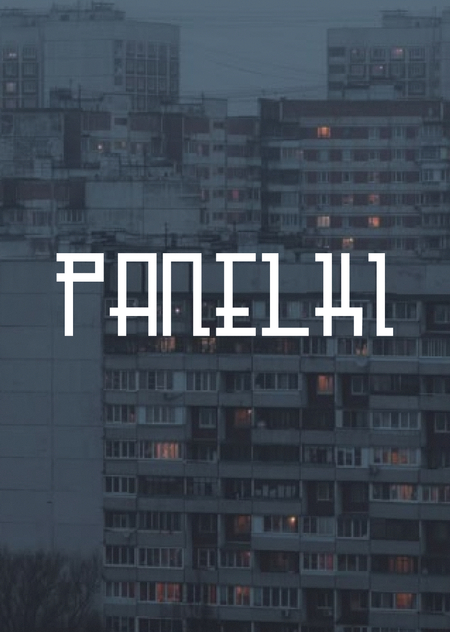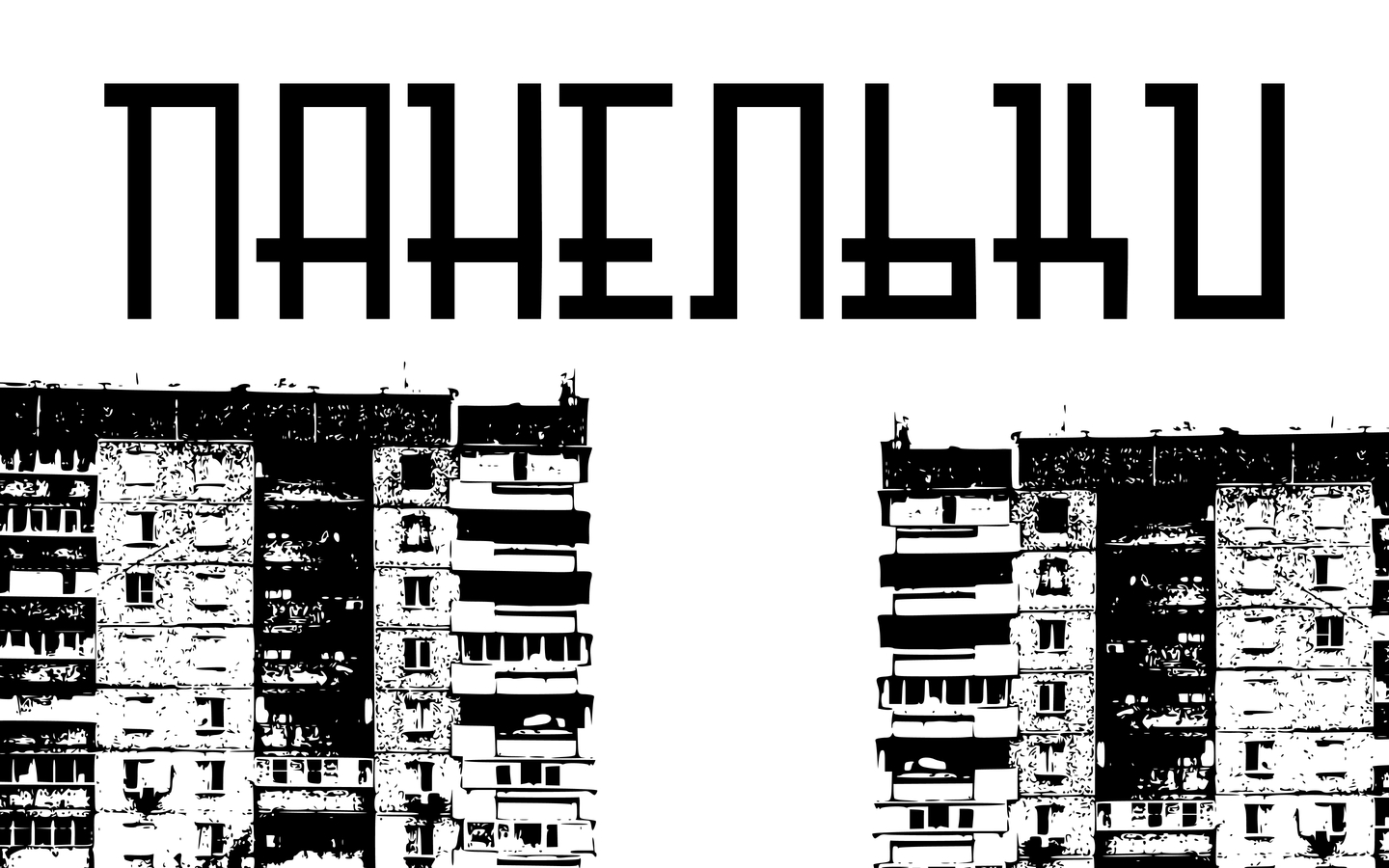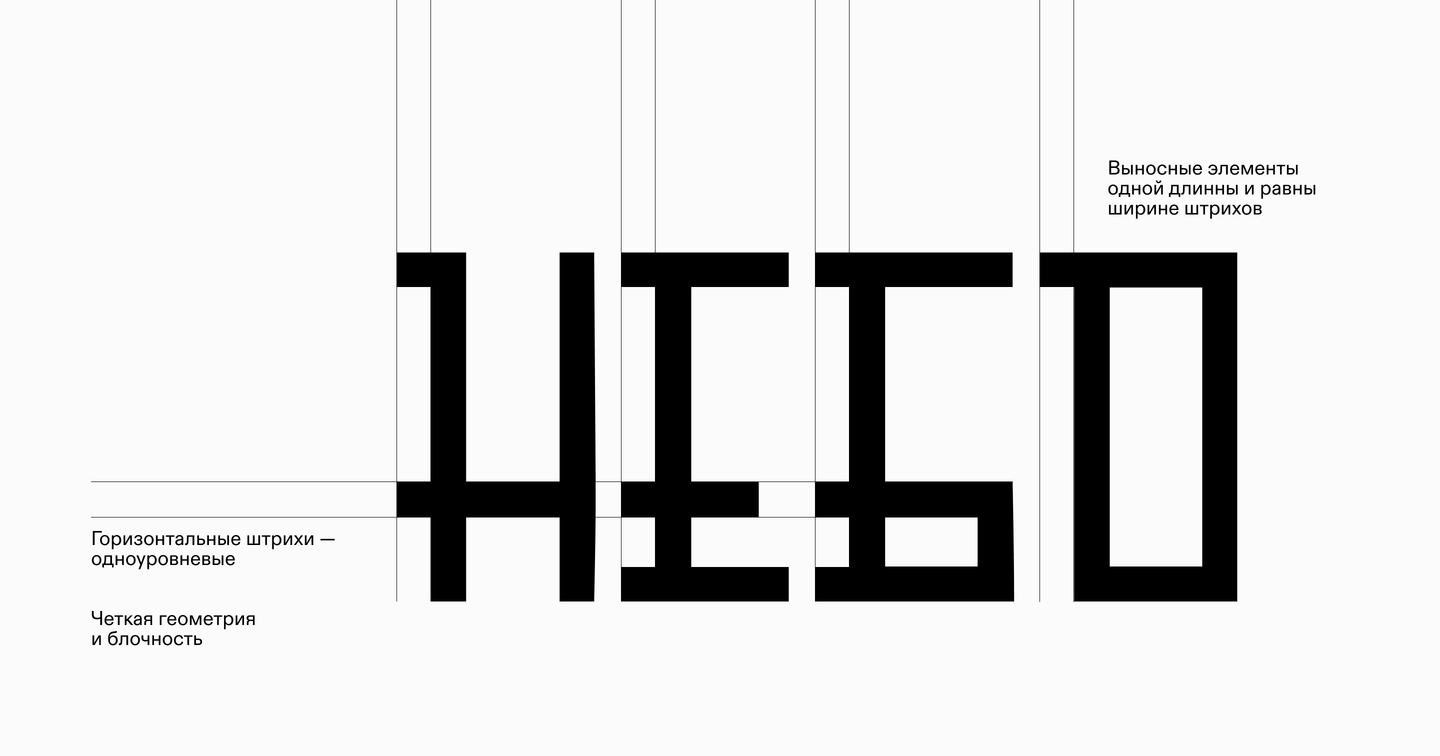
PANELKI — геометричный шрифт с лаконичными формами, вдохновлённый эстетикой советских панельных районов. В его характере — строгость архитектурных ритмов, утилитарность вывесок и сдержанная индустриальная выразительность. Прямые линии, простые пропорции и угловатость создают ощущение функциональности и ностальгии по городскому пространству панелек.